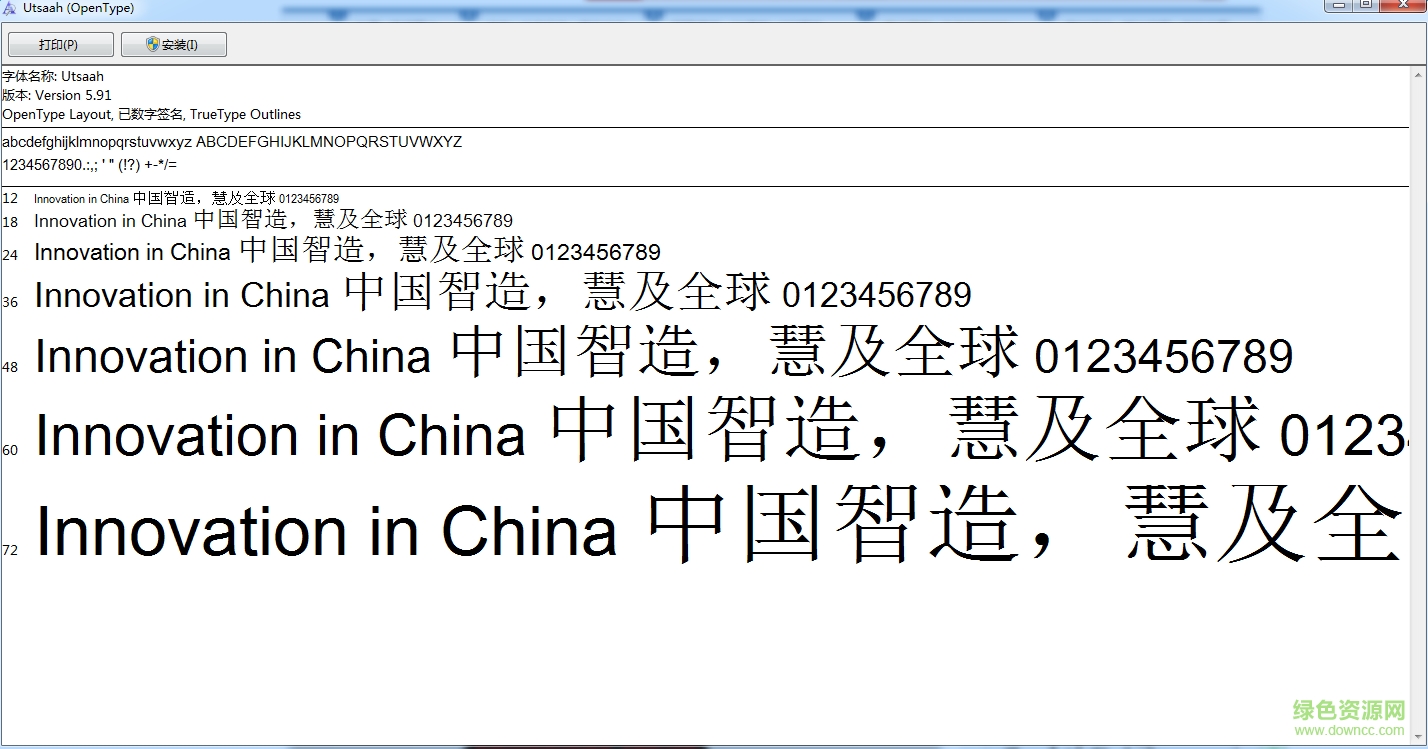
utsaah字體是一款字型圓潤(rùn)飽滿的英文字體,字體筆形清晰,柔軟流暢,整體看上去清秀工整,實(shí)用性非常強(qiáng),喜歡的朋友歡迎在綠色資源網(wǎng)下載收藏!
utsaah字體字形精美俊逸,線條變化自然,可適用于報(bào)紙、雜志、廣告、影視、包裝、ppt等眾多領(lǐng)域!